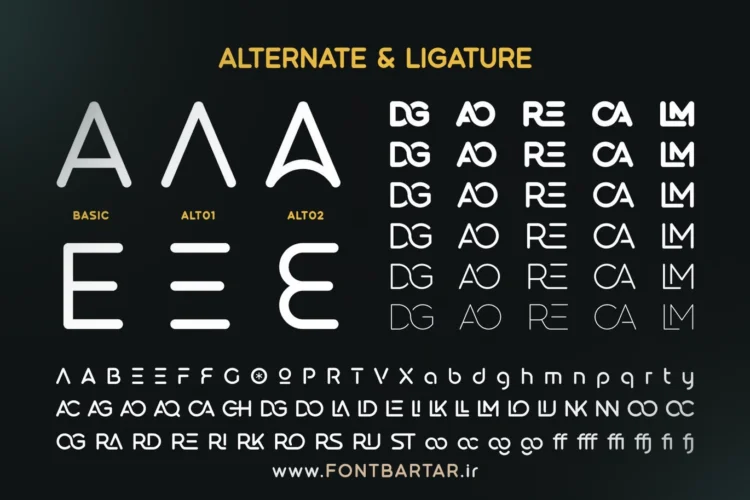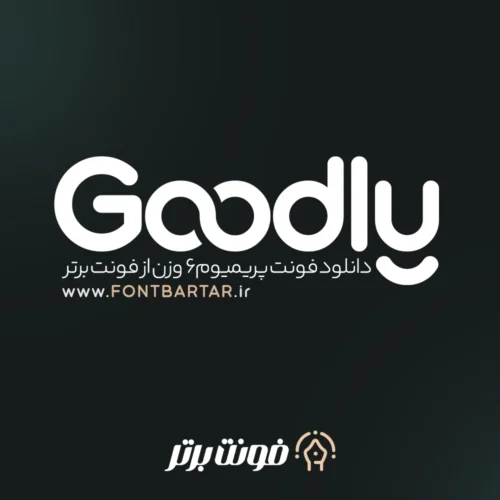
دانلود فونت پریمیوم Goodly یک خانواده فونت انگلیسی بدون سری گرد مدرن است که از 6 وزن سبک تا سنگین تشکیل شده است. می توانید از آن برای ایجاد تعادل طراحی عالی بین مدرن و آسان استفاده کنید. شکل گرد آنها می تواند یک احساس دوستانه ایجاد کند، اما آنها همچنین حرفه ای به نظر می رسند. فونت انگلیسی کلاسیک برای طرحهای لیبل بستهبندی مرسوم، لوگوها و برندهای منحصربهفرد، طرحهای پوستر، مد و بسیاری موارد دیگر مناسب است.
ویژگی های فونت انگلیسی خاص:
- 6 وزن متفاوت
- بهترین فونت انگلیسی گلیف استاندارد
- جایگزین های سبکی و لیگاتورها
- نماد و نقطه گذاری
- چندین زبان پشتیبانی می شود.
فونت انگلیسی فانتزی مناسب برای :
- فونت انگلیسی برای لوگو